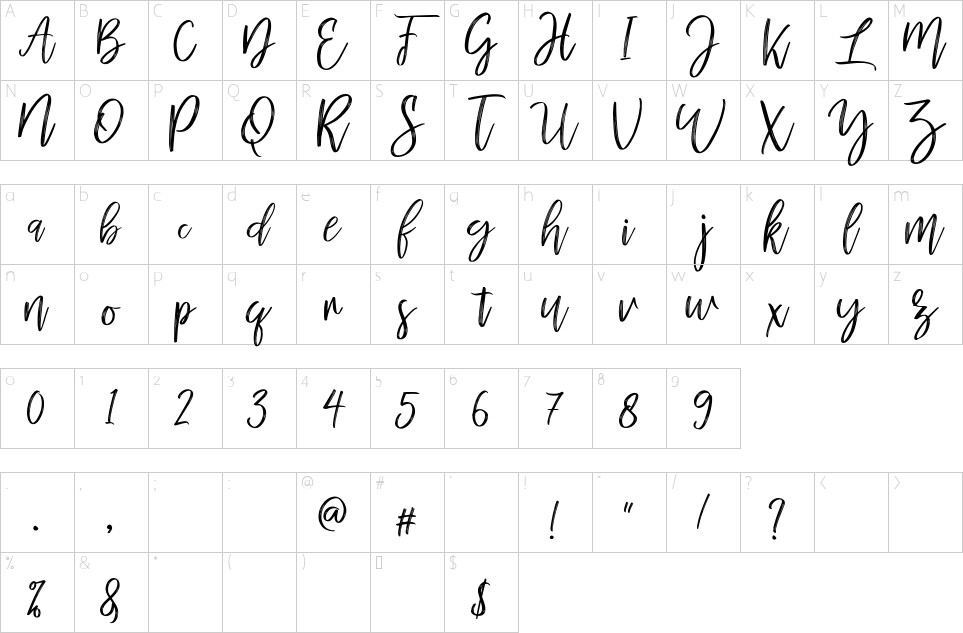
Descubra a frescura das artes digitais com Mellony Dry Brush Font, uma deliciosa mistura de estilo moderno e elegância vintage. Desenhada pelo talentoso Alit Design, esta fonte garante um touch único à sua tipografia. Com suas linhas ágeis e bordas arredondadas perfeitamente realçadas pela técnica da “dry brush”, Mellony Dry Brush traz uma sensação de liberdade para a escrita digital, permitindo que você expressione o seu próprio jeito. Seja para aplicativos empresariais ou criações artísticas, essa fonte garante um toque autêntico e impecável à qualquer projeto. O download é seguro e simples, com versões compatíveis tanto para Windows quanto para Mac, fazendo do seu trabalho de design mais fácil e prático. Com 165.516 downloads confirmados, não há dúvida que essa fonte está ganhando o coração dos designers digitais. Aqui está um pedacinho de tecnologia que combina a essência moderna com a serenidade vintage, sem perder sua personalidade única. Descubra seu próprio estilo hoje!